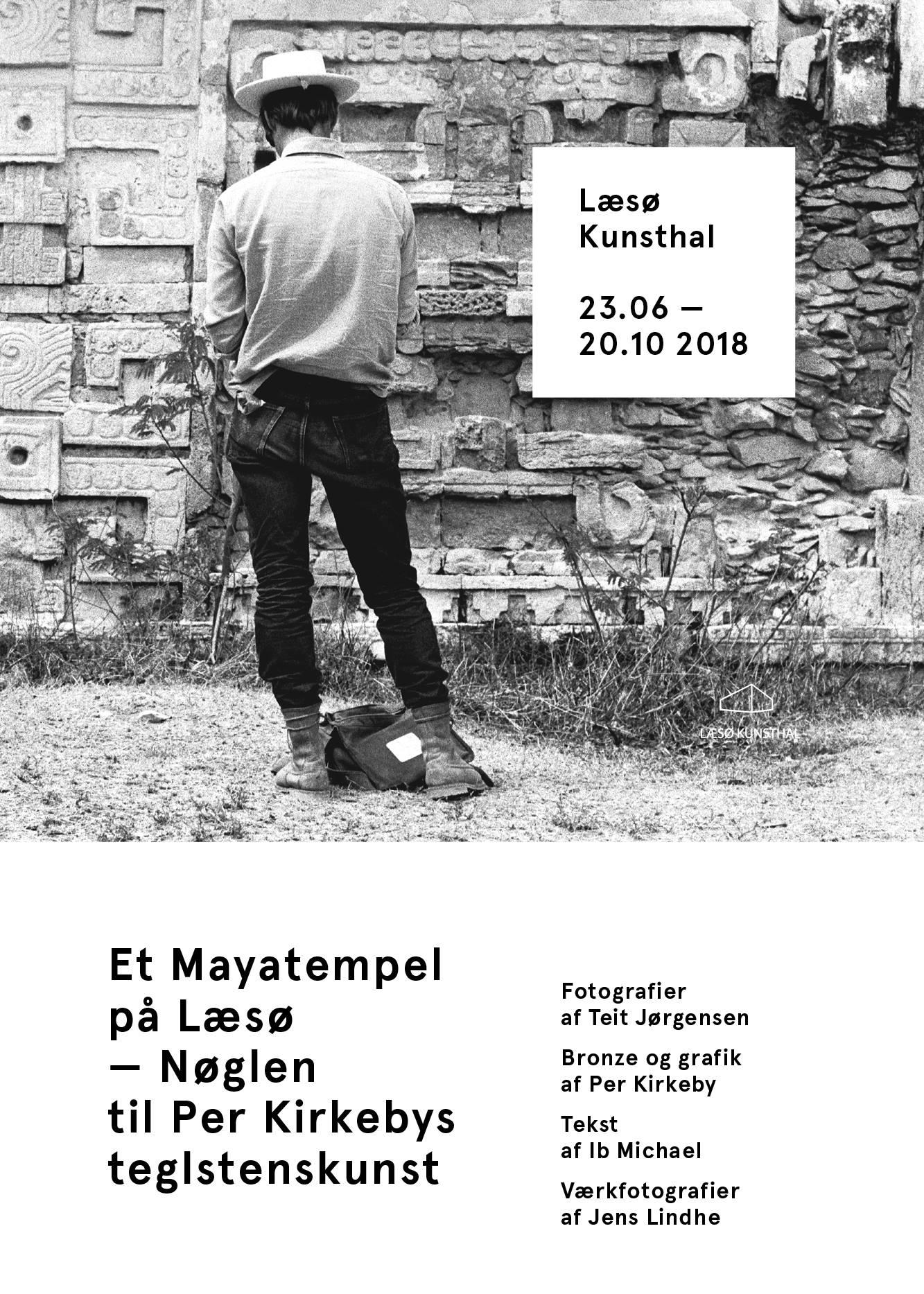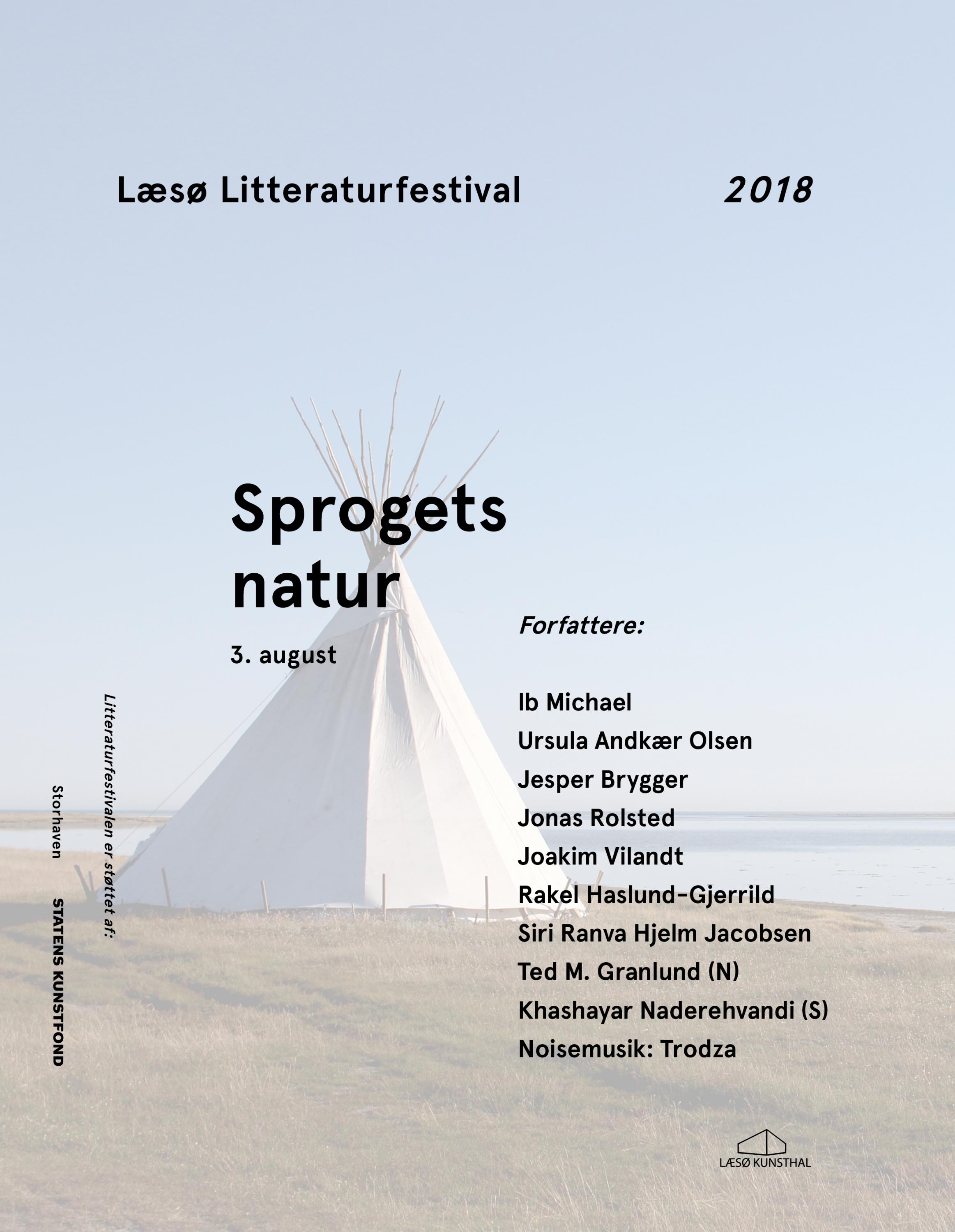
Suche Grotesk vom aktuellen Læsø Kunsthal Poster. Sehr knyffelyg.
bisher hats mit den mir bekannten Mitteln meist gut geklappt, gelegentlich gabs Treffer bei WhatTheFont etc. oder es half der Blick in die Website-Ressourcen, bzw. ein verfügbares PDF. Jetzt steh ich auf dem Schlauch.
Ein Poster und ein Flyer, die Schrift klebt aktuell auch ausgeplottet auf der Eingangstür der Læsø Kunsthal - ich könnte diese Woche noch ein Bild nachreichen, wenn die Anhänge nicht langen. Vor Ort konnte mir leider niemand helfen.
Als Amateur fehlen leider die Skills, diesen Font genauer zu klassifizieren. Ähnlichkeiten sehe ich bei der LL Circular, auch der Avenir, demnach eine geometrische Antiqua?
Anfangs habe ich Schrifttypen mit geschlossenem 'a' verworfen - die geöffnete Variante könnte auch aus einem OT-Style stammen? Wie auch immer, Ähnlichkeiten ja, aber kein Volltreffer.